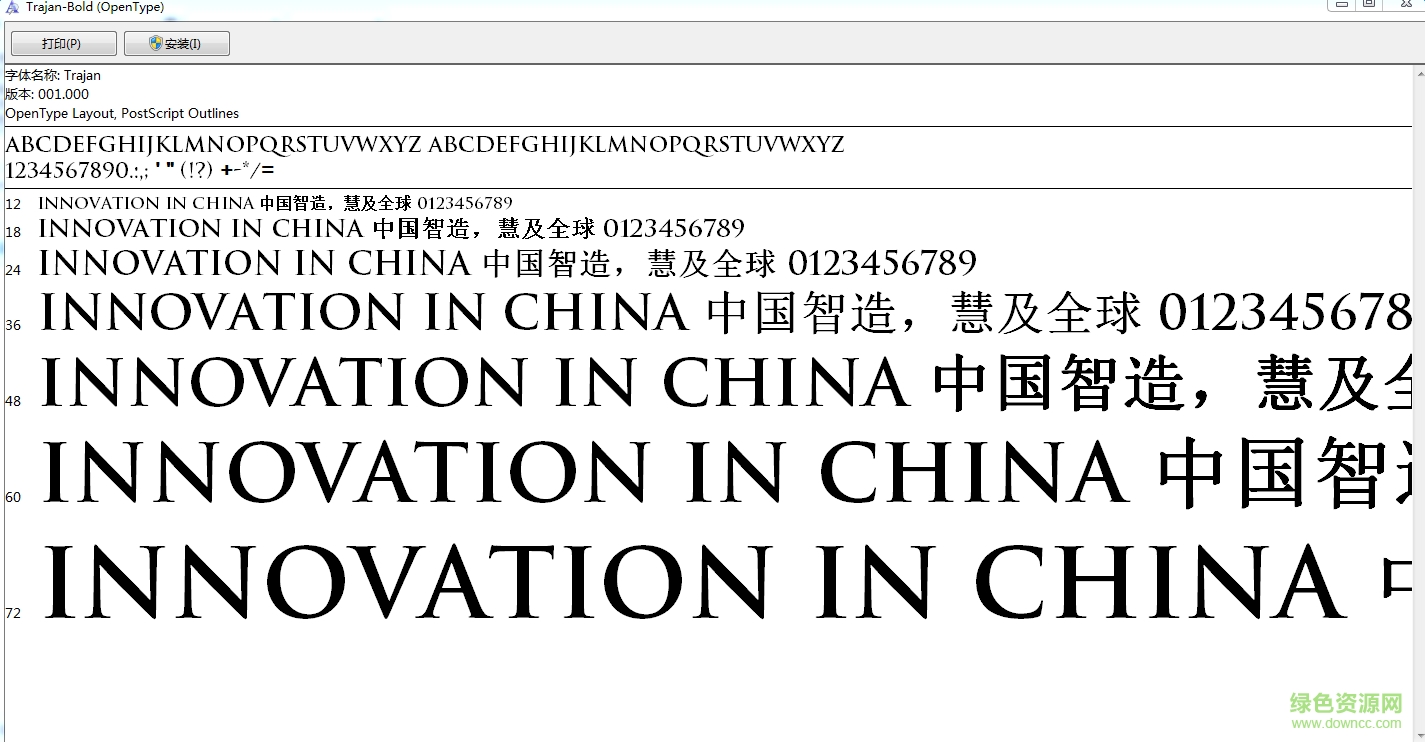
trajan bold
trajan bold字體是一款全是大寫的英文字體,該字體筆致遒勁,厚實(shí)有力,形如雕刻,常用于各類海報(bào)設(shè)計(jì)中,需要該字體的朋友歡迎在綠色資源網(wǎng)下載!
Trajan字體介紹
Trajan是一種舊襯線體字體,源于羅馬帝國(guó)的石碑雕刻。Trajan只有大寫部,大小寫僅通過(guò)字母的大小區(qū)別。Trajan“字母寬度差別很大,字型端莊、氣勢(shì)恢宏,充滿了歷史厚重感”,在好萊塢電影海報(bào)設(shè)計(jì)中相當(dāng)流行,用在PPT的封面中效果也非常不錯(cuò)。當(dāng)然,使用這種只有大寫部的字體來(lái)顯示大段文字是很讓人抓狂的!